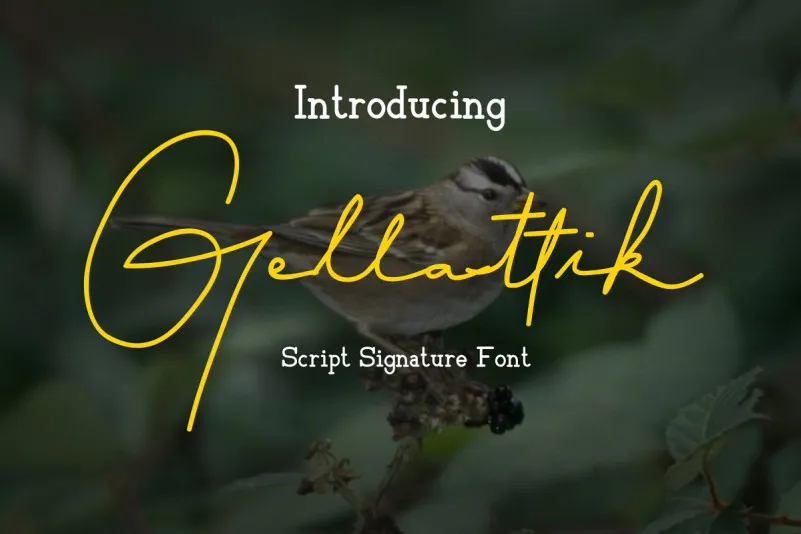
Gellattik Signature Font – Fonte Grátis
Gellattik Signature Font
A Gellattik Signature Font é uma fonte moderna e elegante criada pela AnomaliDesign. Este recurso do M.0Type oferece um estilo script que transmite elegância, naturalidade, sofisticação e perfeição para qualquer projeto que exija o toque de escrita à mão. Essa fonte é uma excelente escolha para aqueles desejando incorporar um elemento autêntico e moderno em seus projetos. Ela transmite uma sensação fresca e não formal, mantendo a sofisticação necessária para qualquer projeto profissional ou criativo. A Gellattik Script é perfeita para design de websites, criação de logotipos, embalagens personalizadas, gráficos de mídia social, entre outros formatos. Suas linhas fluidas e seu toque casual fazem com que esta fonte seja um recurso valioso para qualquer designer gráfico buscando expressar elegância e naturalidade em seus trabalhos.